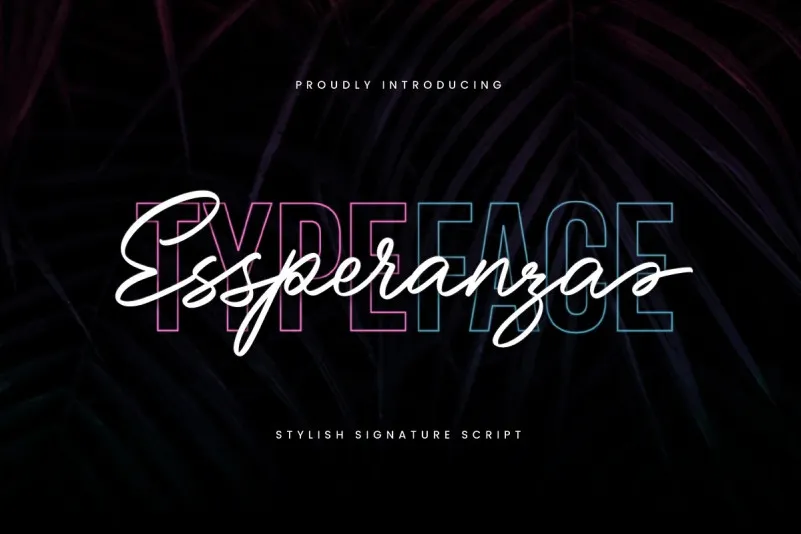
Essperanza Font – Download Grátis
Essperanza é uma bela fonte de letra script criada pela Creatype Studio. Com seu design meticulosamente inspirado na escrita manuscrita, Essperanza oferece um toque natural que permite sua aplicação em diversos meios de comunicação. Esta fonte é ideal para textos legíveis e elegantes, perfeita tanto para títulos quanto para subtítulos. Suas linhas fluidas e detalhes mínimos tornam essa fonte uma escolha versátil que pode dar vida a qualquer projeto gráfico. Essperanza é especialmente adequada para aplicar em websites, design de logotipos, criação de materiais de mídia social e muito mais. Em um mundo cada vez mais digitalizado, Essperanza mantém o espírito humano da escrita com sua simpatia e versatilidade, tornando-a uma fonte indispensável para qualquer designer em busca de personalidade e originalidade nos seus projetos.